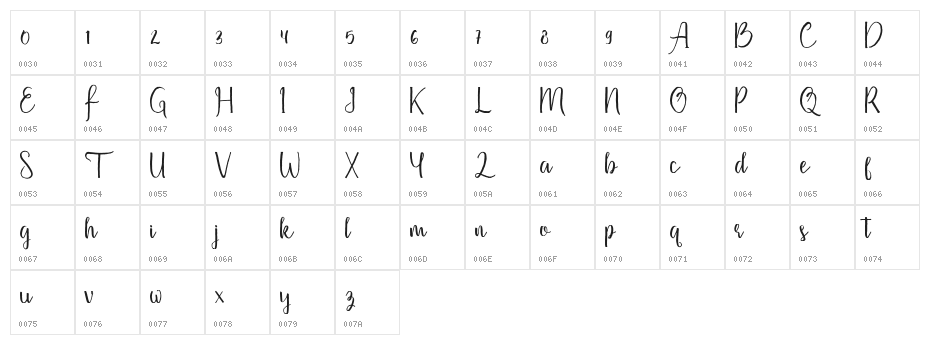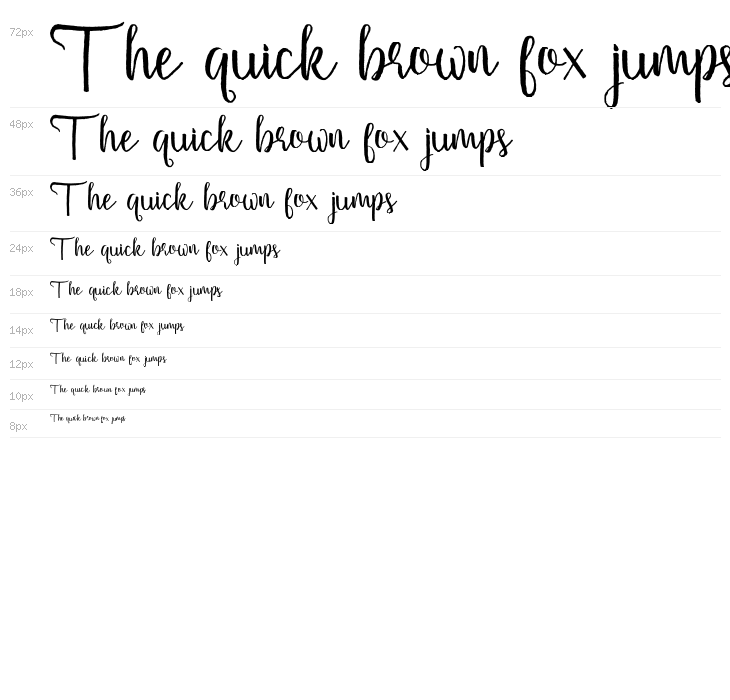
Firdaus Font
| Stile generale | Casual |
| Caso d'uso | Logos, Invitations, Greeting Cards |
| Progetti proposti | Ideal for greeting cards, invitations, personal branding, and creative projects requiring a personal touch. |